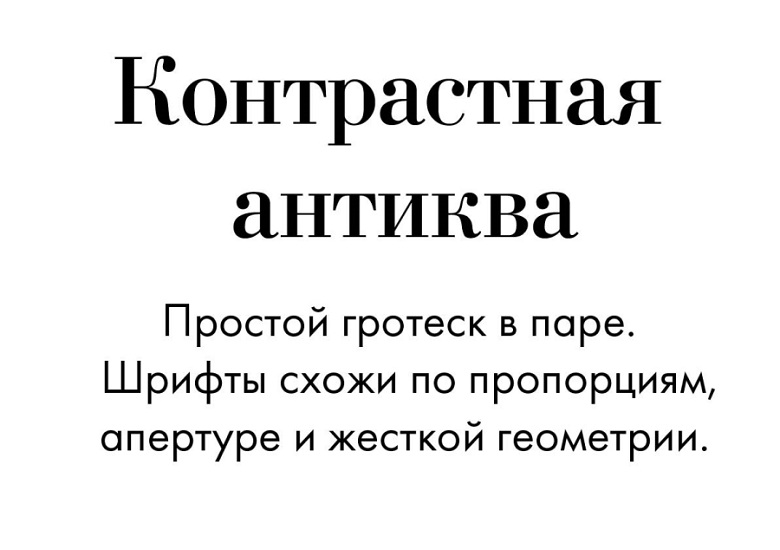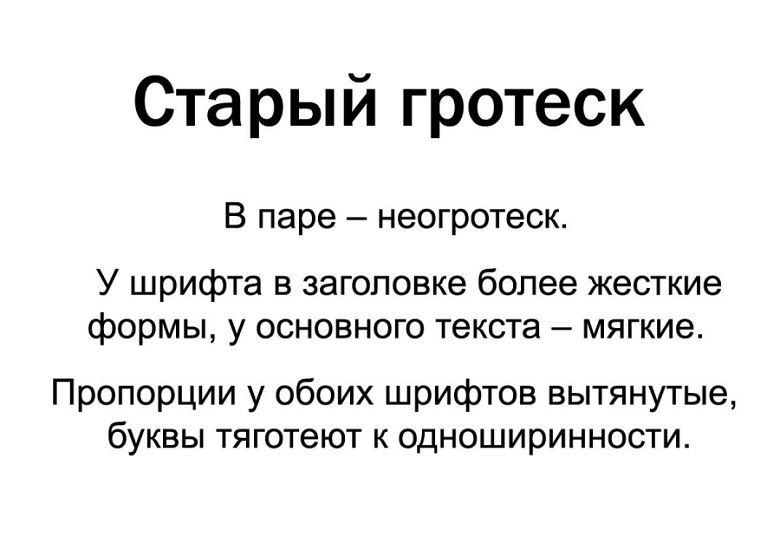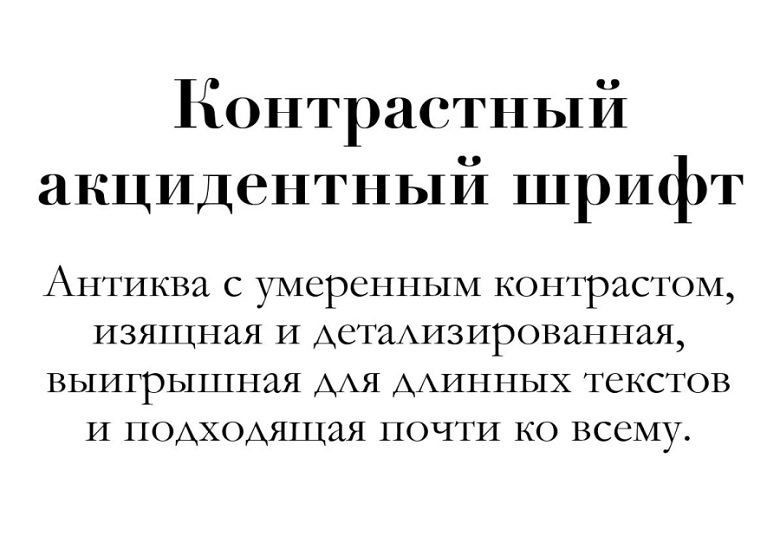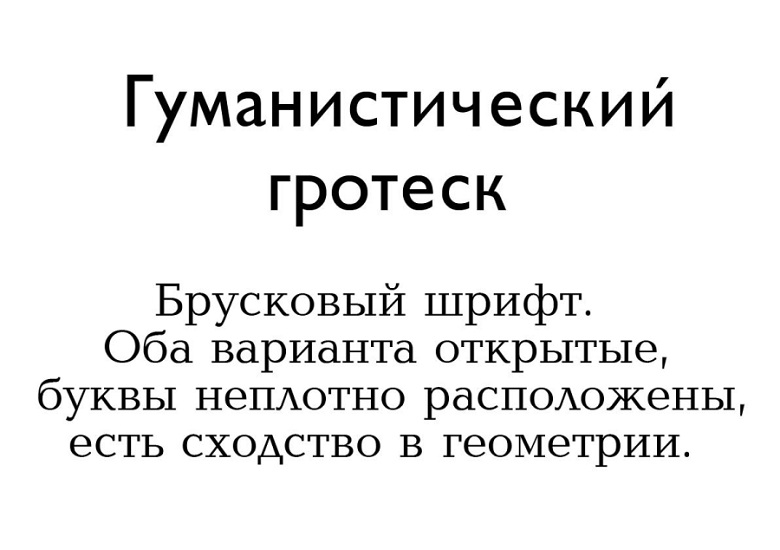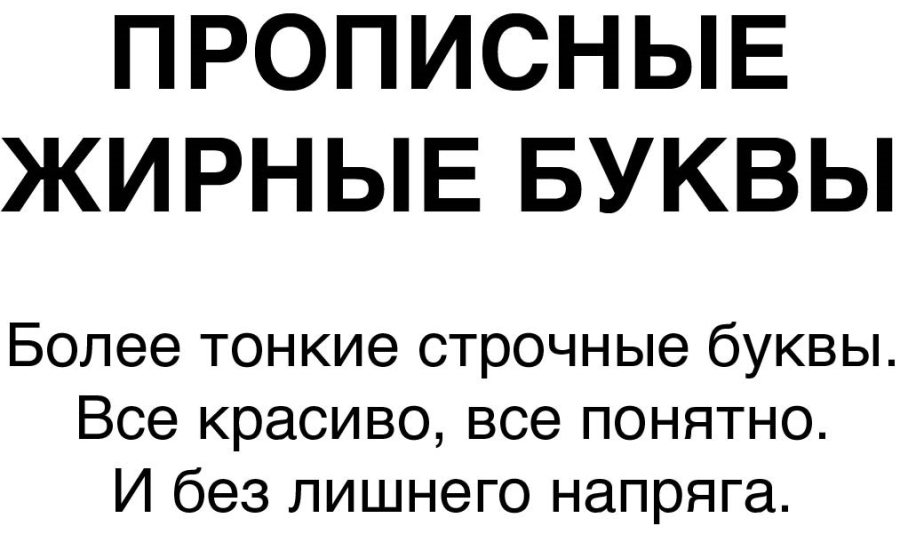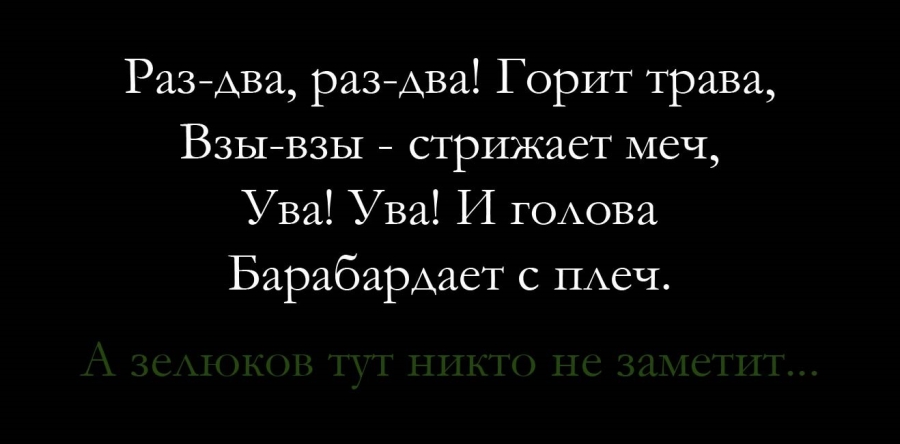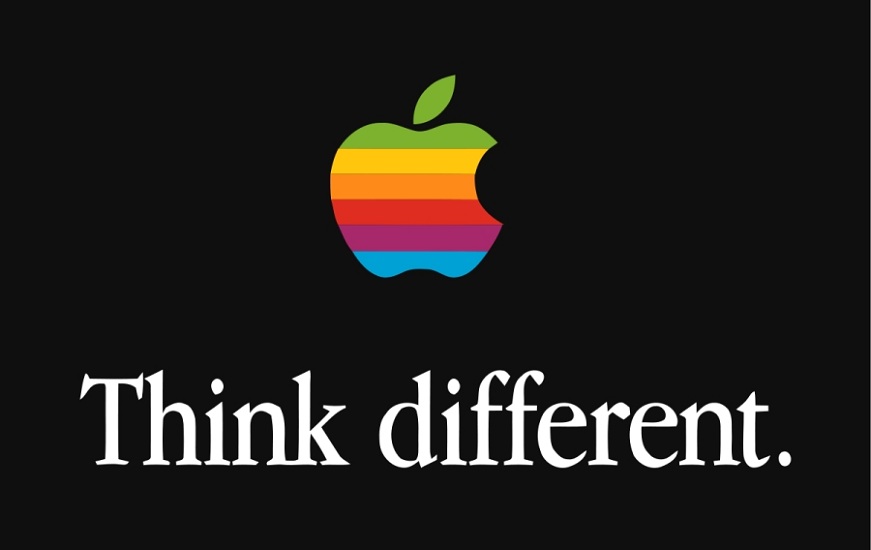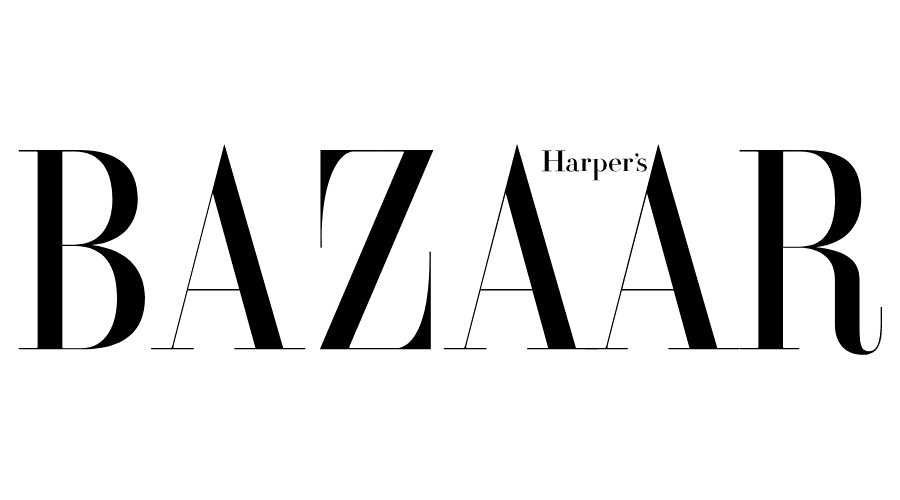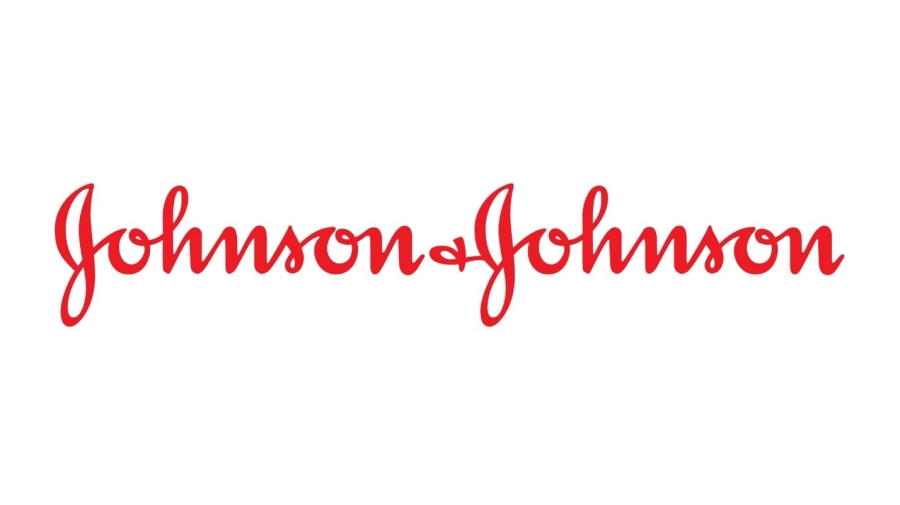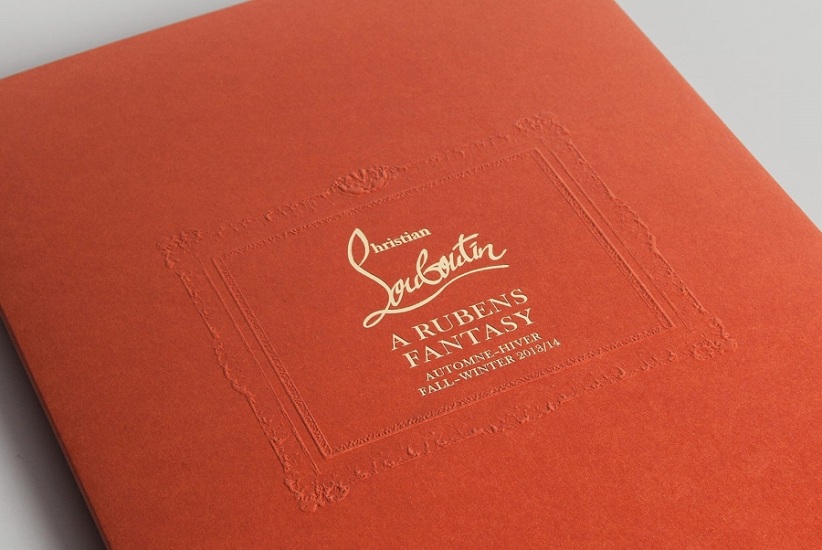
Если конкурентные компании обменяются шрифтами, выбор между «Колой» и «Пепси» станет для потребителя еще сложнее
Знания в типографике актуальны не только для узких специалистов. Они пригодятся маркетологам, предпринимателям и менеджерам: если вы собственноручно набираете тексты или затрудняетесь оценить готовый дизайн. Я рассмотрю способы оформления надписей, виды шрифтов, правила их сочетания и тренды в брендинге.
Обычно оформление текста начинается с выбора шрифтов. Их все можно разделить на пять групп:
Знакомьтесь, так они выглядят
А это критерии их различия:
• У антиквы значительно разная толщина штрихов и наличие засечек.
• У гротесков – единая толщина и отсутствие засечек.
• Брусковые шрифты – это ребята с простыми широкими засечками и малозаметной разницей в толщине штрихов. Промежуточный вариант между антиквой и гротеском.
• У рукописных (еще их называют псевдорукописными, каллиграфическими или скриптами) – сглаженные углы и присутствие соединительных штрихов.
• Декоративные – это плод больного или здорового воображения художников. Они никаким правилам не подчиняются.
Теперь давайте пройдемся по всем и посмотрим на примеры.
Это первое типографическое достижение человечества. Для латинского алфавита антикву разработали в 15 веке. Шрифту предшествовало письмо от руки: поэтому у всех букв есть засечки, а начертания основаны на дуктальном принципе – есть тонкие и толстые линии, как от движения пера.
Антиква старого стиля. Apple использовали шрифт Garamond. Он живой, детализированный, с умеренным контрастом между толщинами линий, знаки открытые (обратите внимание на “e”)
В 17 веке в эпоху барокко антиква трансформировалась – контраст толщин увеличивался, линии становились более жесткими и механистичными, внешне буквы все более отдалялись от рукописных.
Переходная антиква эпохи барокко на обложке каталога с «лабутенами»Еще пример переходной антиквы: британский шрифт Caslon, созданный в начале 18 века
В конце 18 века для французских революционных плакатов начали создавать антиквы нового стиля. Сейчас такие шрифты часто используют в заголовках и логотипах.
У новых антикв огромная разница между толщинами в буквах – это хорошо в большом масштабе для привлечения внимания
Они с нами сравнительно недавно. В 19 веке их начали активно применять для газетных заголовков, плакатов и афиш – такие буквы были четко различимы издалека. К началу 20 века их стали брать и для набора больших текстов: форма начертания тут проще, чем в антикве, и печать обходилась дешевле.
Сейчас гротески повсеместно нас окружают и никакого удивления не вызывают.
Это Franklin Gothic, который относится к старым гротескам. Овалы вытянутые, все буквы закрытые и тяготеют к одной ширине.
Конструктивисты экспериментировали с гротесками в 30-е годы, пытаясь превратить буквы в геометрические фигуры. Им больше нравились квадраты и прямоугольники, но в наше время особенно популярны шрифты на основе круга.
«Округлые» гротески – это своеобразный маркер нашего времени. Такие шрифты считаются располагающими, дружелюбными, демократичными. Присмотритесь: они везде!
Антитеза конструктивизму – гуманистические гротески:
Они немножко похожи на антикву: толщина основных и соединительных линий заметно различается
В 50-х годах возникли неогротески. Они развивались в традициях швейцарской школы – это стандартные, незаметные, функциональные шрифты, обычно имеющие много вариантов начертаний.
Самый популярный неогротеск – Helvetica. Нейтральный шрифт, который подходит для любых ситуаций
Брусковые буквы развиваются с 19 века. Для гротеска в них слишком явная разница толщин и мощные засечки. Для антиквы – разница толщин слишком маленькая, а засечки слишком грубые. В итоге вышел гибрид – странный, но симпатичный.
Некоторые брусковые шрифты развивались из антиквы, другие – из гротесков. Тут представлен первый случай
Еще есть рукописные шрифты (скрипты), их ни с чем не спутать. До изобретения клавиатуры человеку важна была скорость письма, поэтому буквы имеют упрощенную форму и соединения друг с другом – все это характерно и для шрифтов, вдохновленных письмом от руки.
Шрифт Snell в названии фильма Дэвида Линча
Наконец, декоративные шрифты – это все, что не вписывается ни в какие рамки.
Если вы вообще не понимаете, что за шрифт перед вами – значит он декоративный. Такие буквы хороши для заголовков, если использовать их дозированно
Сейчас новые шрифты создаются каждый день, но, как видите, для старых я тоже нашла современные примеры. Многие гарнитуры стали своеобразной классикой, и крупные компании с удовольствием их используют. А вот новые шрифты имеют свойство устаревать – чем сложнее их форма, тем быстрее наш мозг улавливает паттерн и привыкает к нему. И повторное появление шрифта у другого бренда вызовет ощущение дежавю. Поэтому выбирать стоит или старые проверенные шрифты, или совсем свеженькие.